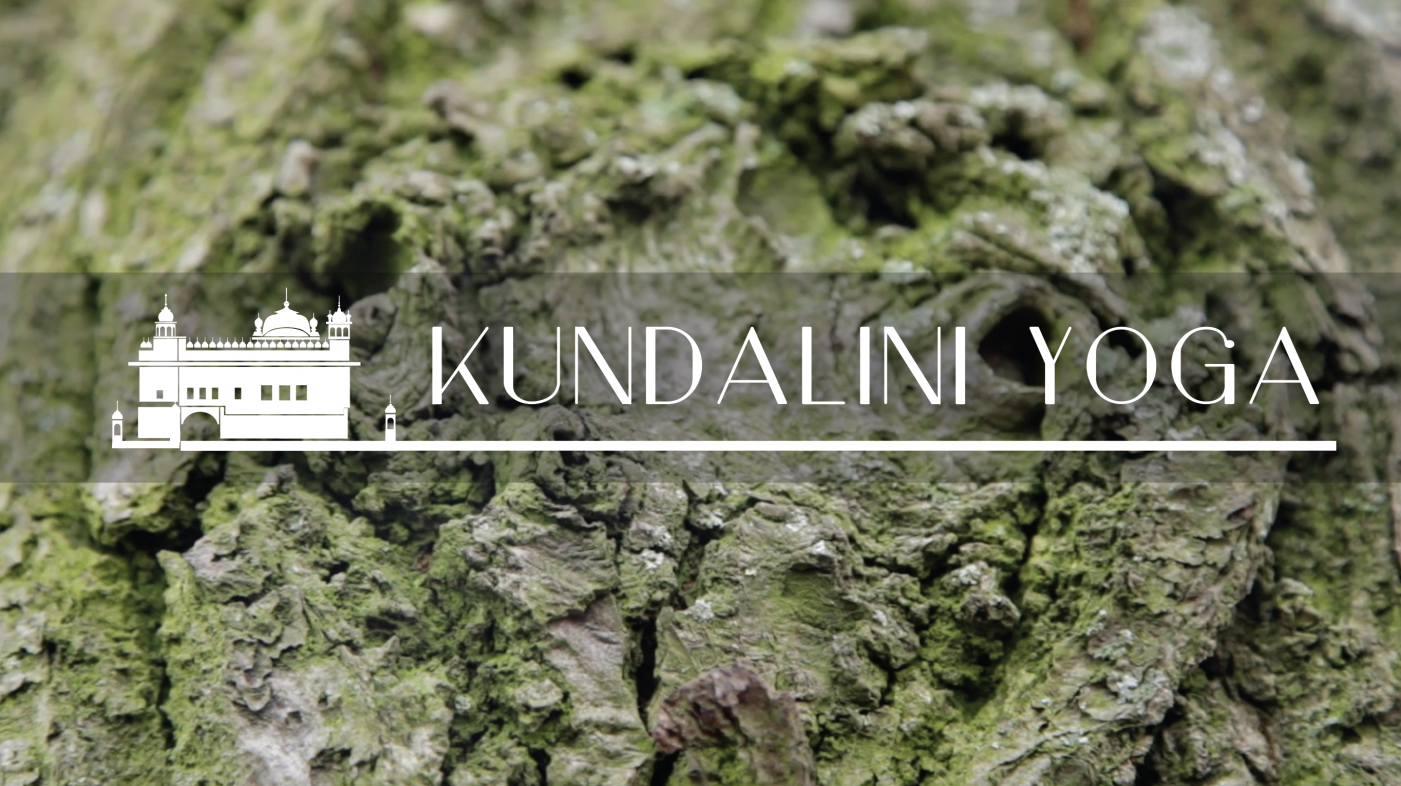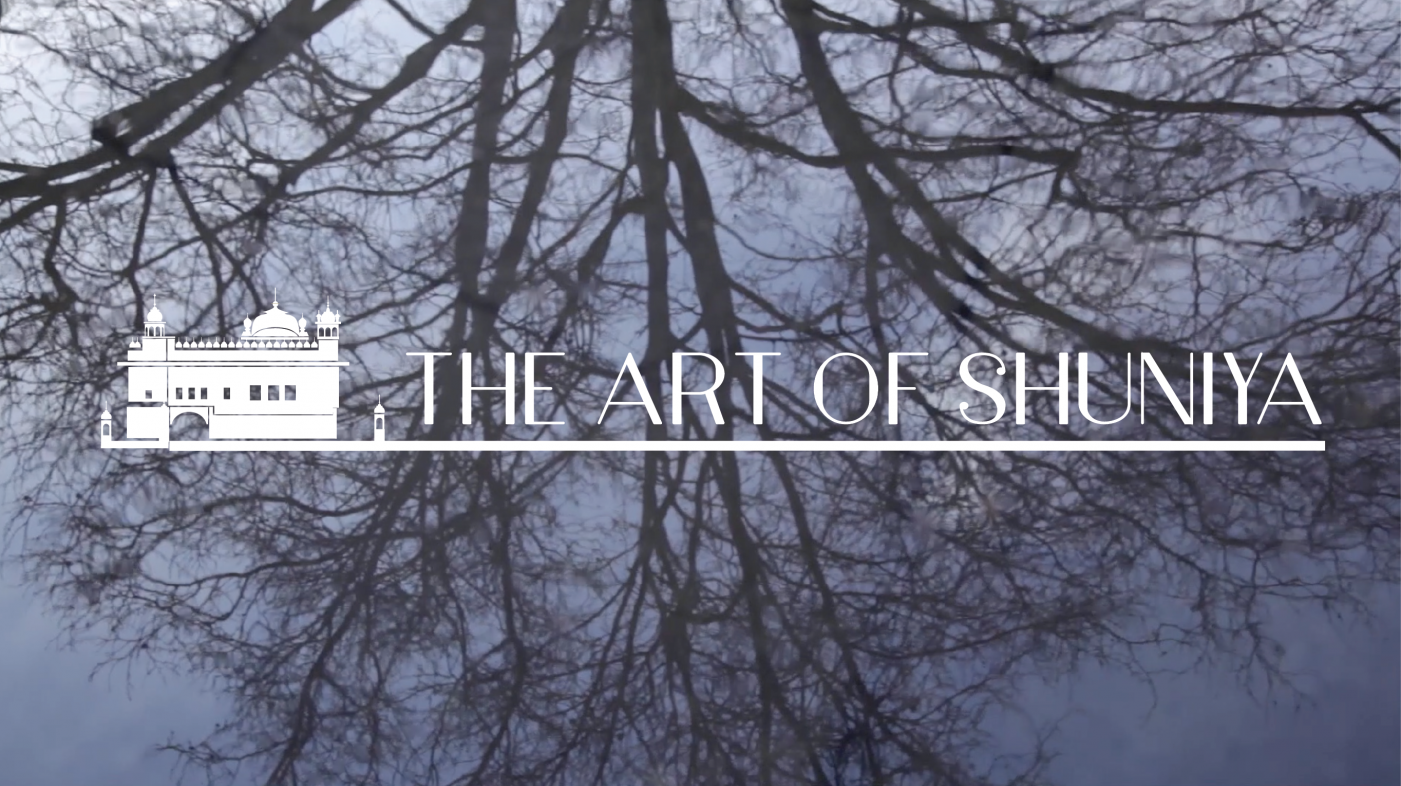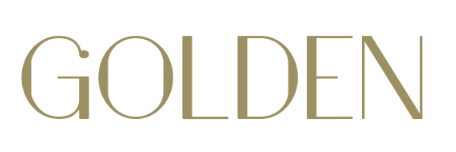
Suche diese Retro-Schrift von Golden Healing
ich bräuchte diese Schrift, um das auf golden-healing.com zu sehende Logo nachzusetzen, da es nur als Pixelbild existiert ... habe schon lange gesucht und das G ist ja auch recht eindeutig, aber noch nichts gefunden - wer hat eine Idee?
Es ist nicht auszuschließen, dass diese 9 Buchstaben extra für das Logo gezeichnet wurden. Ich schätzt mal, das hätte ich unter einer halben Stunde in Corel gebaut.
Es gibt noch weitere, daher gehe ich eher von einem Font aus …
Das fehlende Kerning lässt mich weiterhin vermuten, dass das eher auf dafont und Konsorten zu finden sein wird.